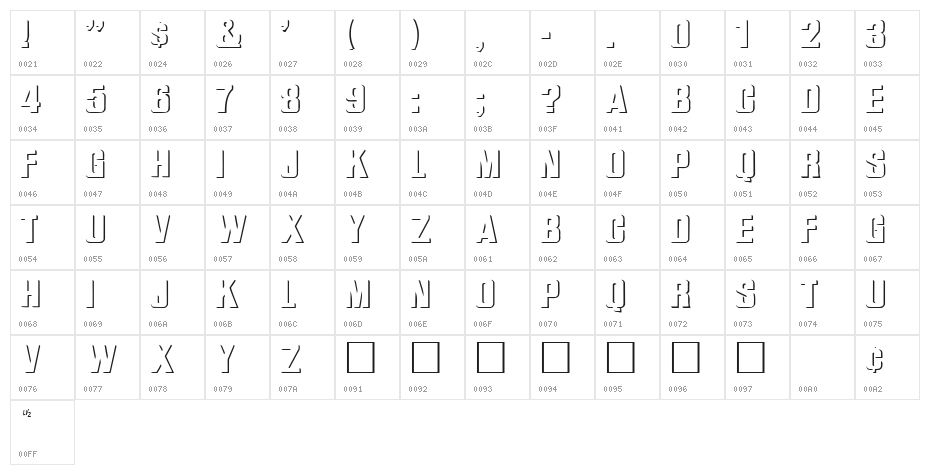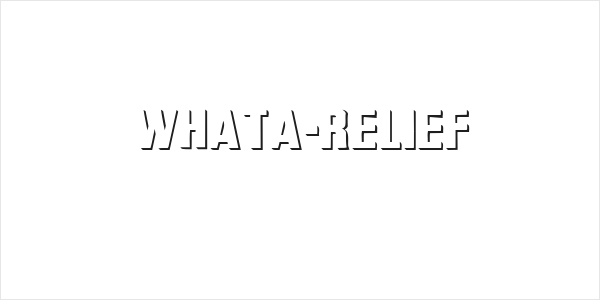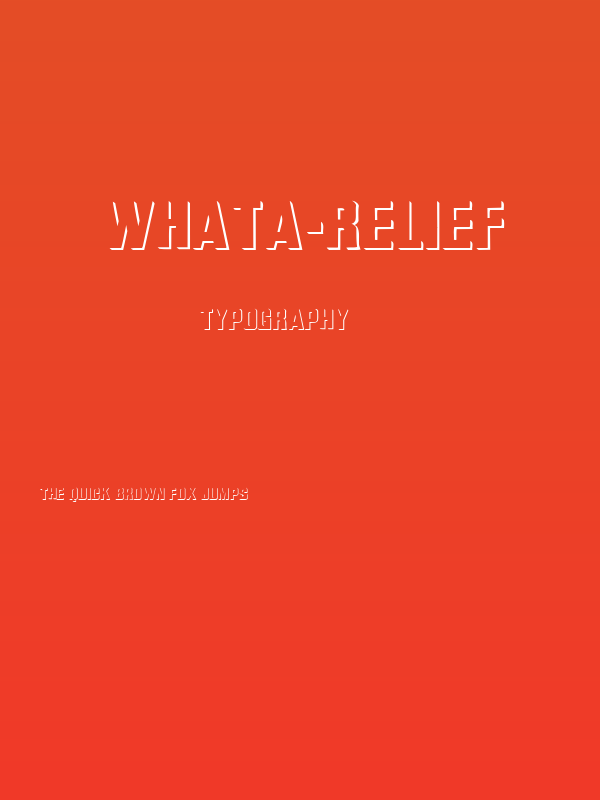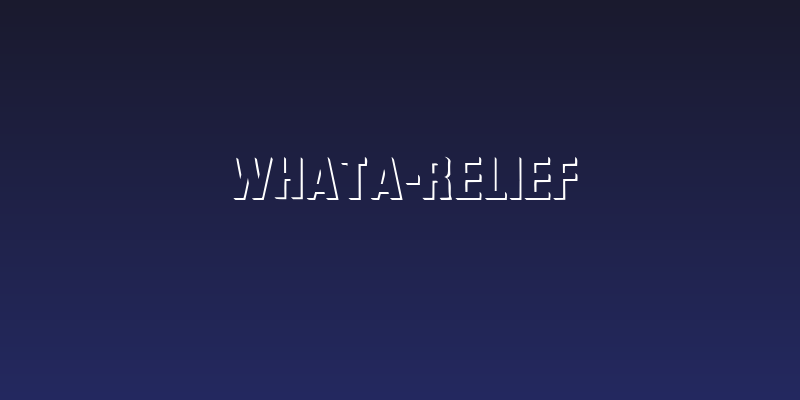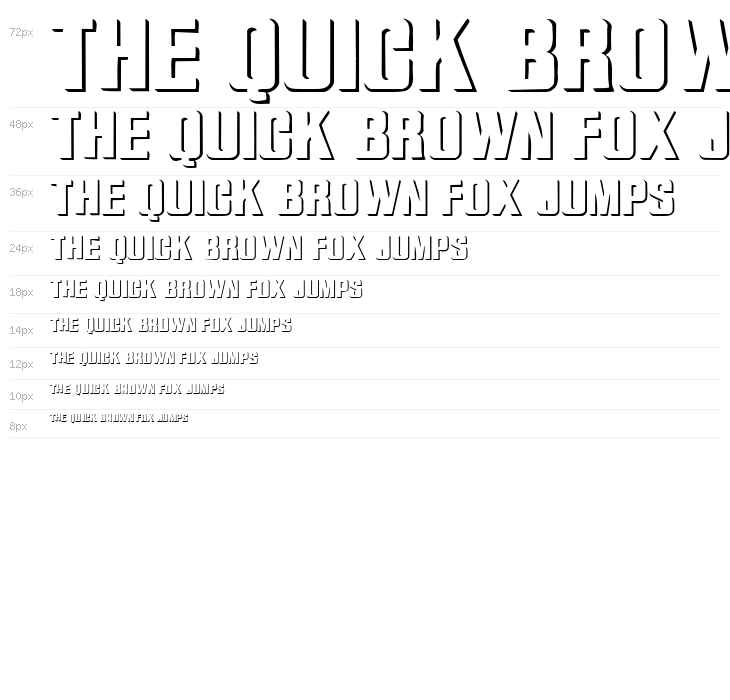
WhatA-Relief Font
| Vorgeschlagene Projekte | This font is perfect for projects that require a strong visual impact, such as posters, advertisements, and branding materials. Its unique style makes it suitable for modern and creative designs. |